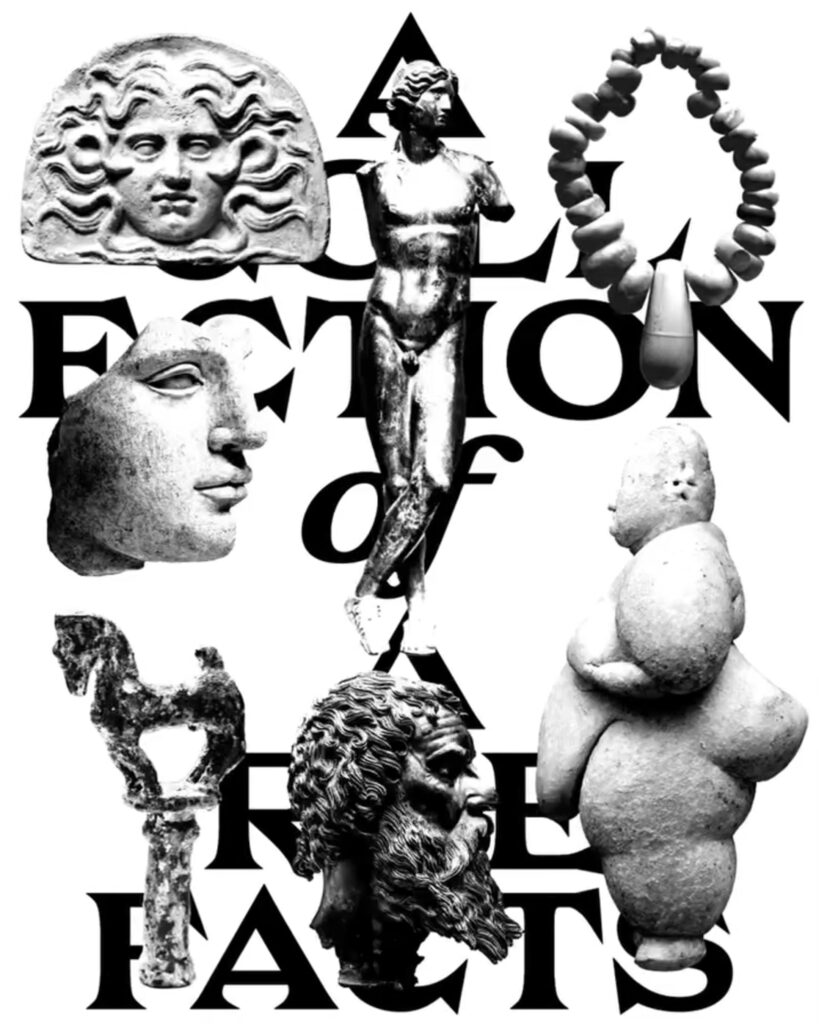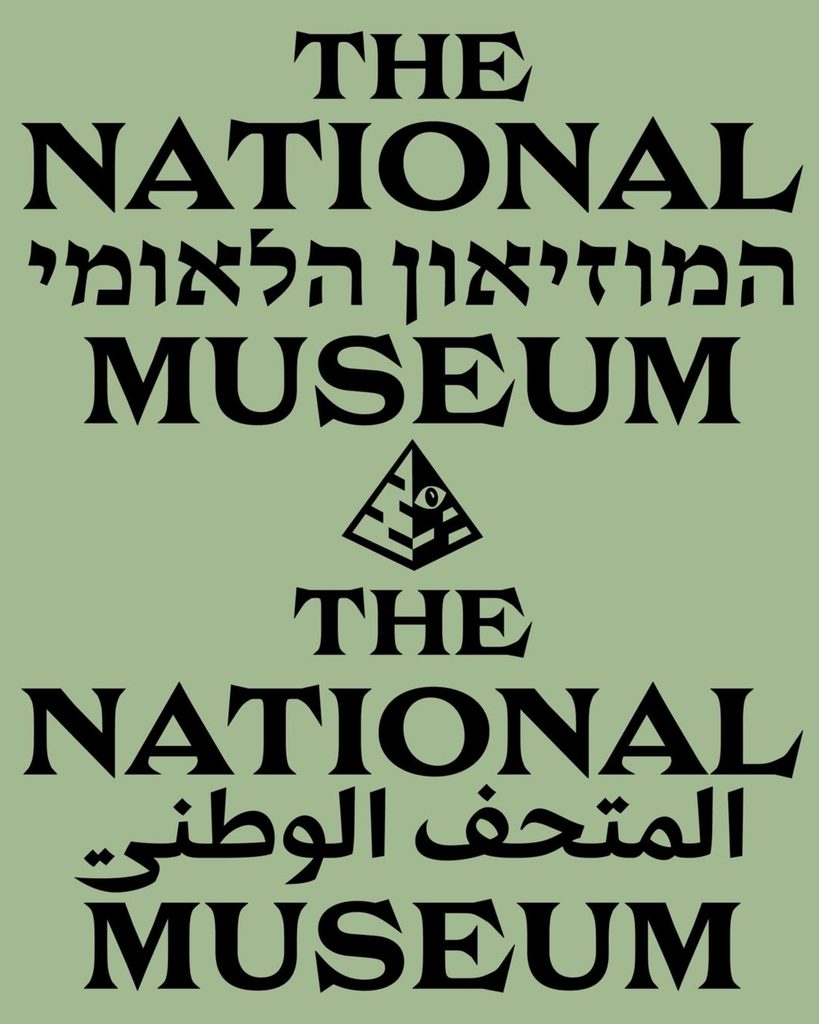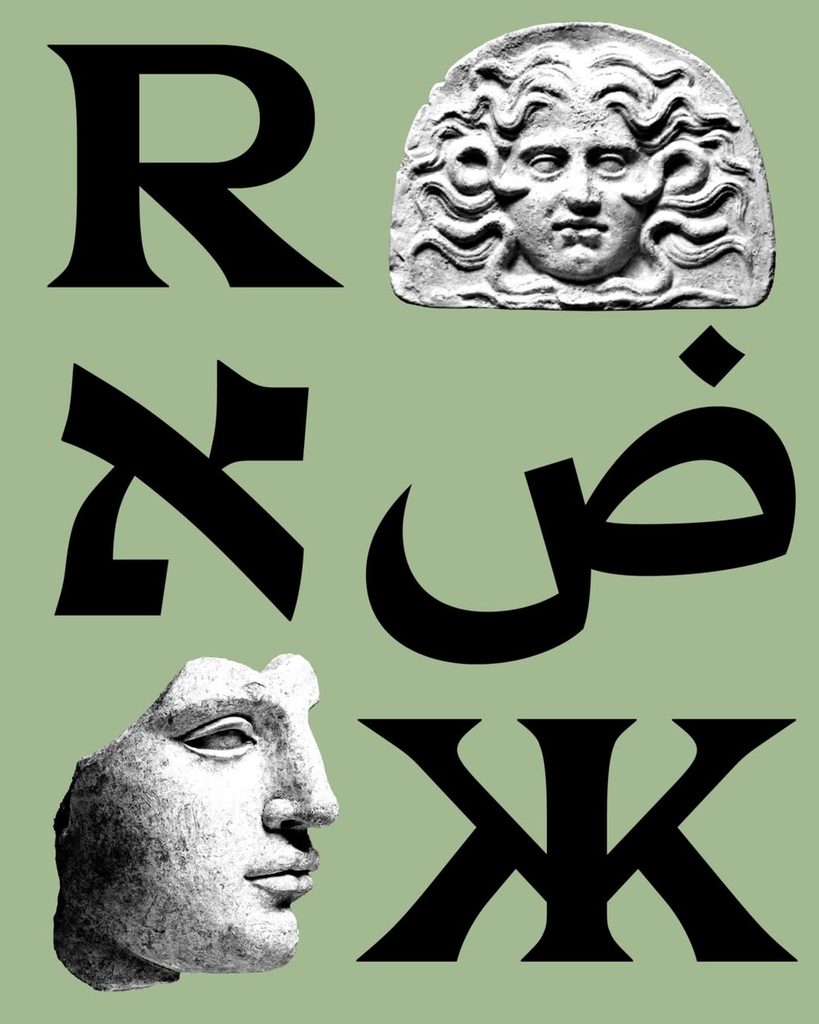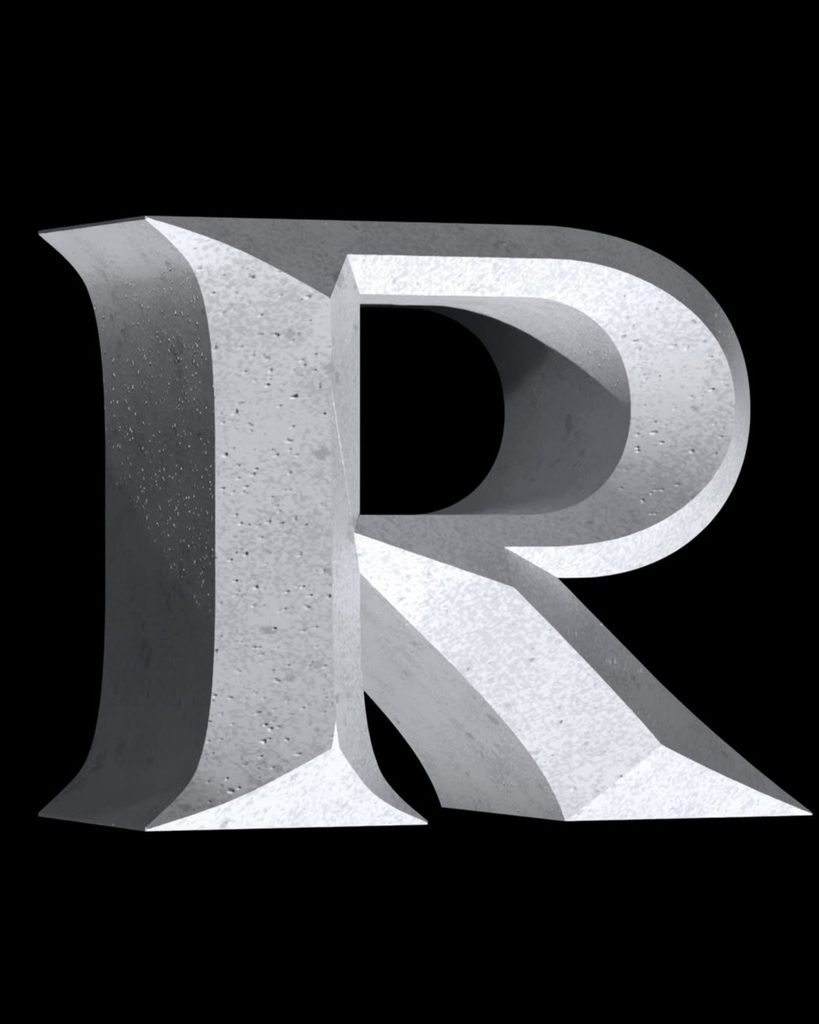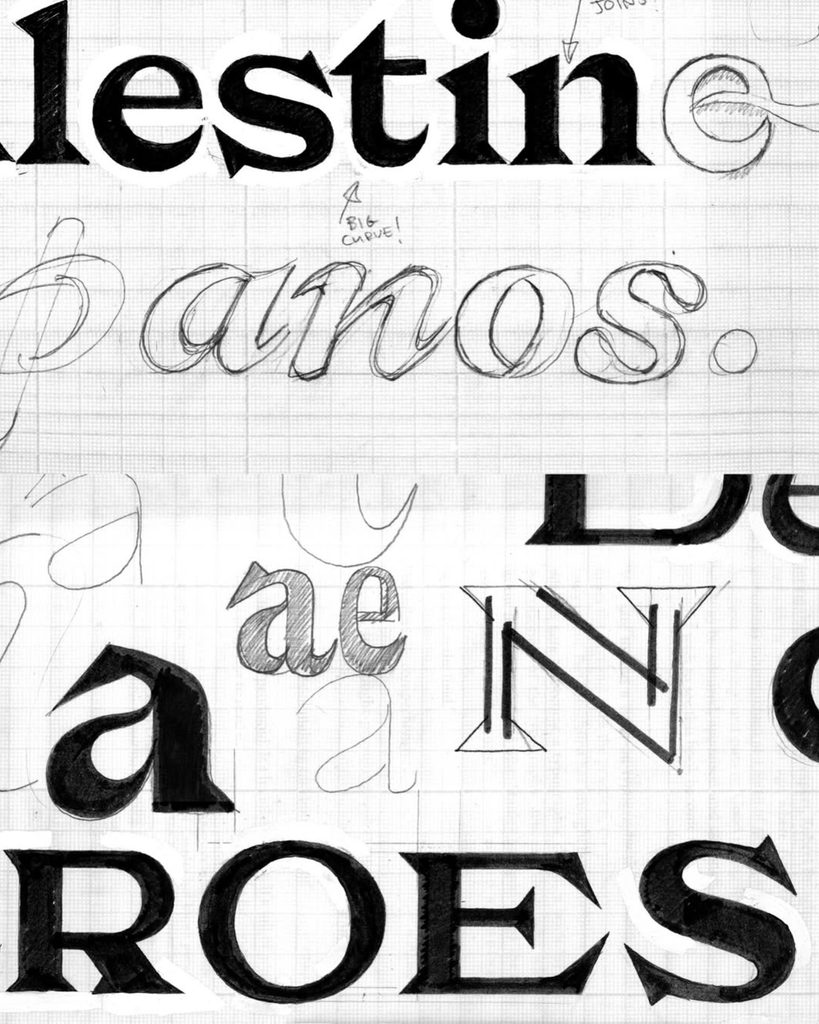
Relic, 디스플레이 서체 히브리 스타일 추가
East of Rome의 디스플레이 서체 Relic에 히브리 스타일이 추가됐습니다. 기존 Relic은 라틴, 키릴, 아랍 문자를 지원하는 제목용 서체로 소개돼 왔습니다. 이번 업데이트로 히브리 문자까지 제품군에 포함됐습니다.
Relic은 묘비 글자와 석재에 새긴 문자에서 출발한 무거운 샤프 세리프 스타일의 타이틀용 서체입니다. East of Rome 공식 소개에 따르면 기존 제품군은 Canonic, Demotic, Arabic 스타일로 구성됐고, 확장 라틴과 키릴, 아랍어권 언어 지원을 포함했습니다.